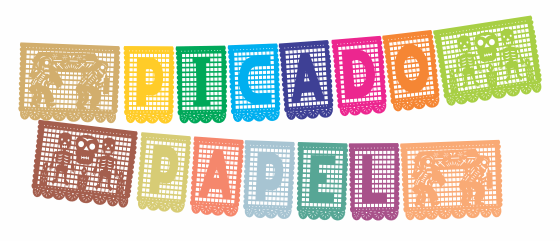
Esta fuente esta inspirada en el papel picado que se usa en México en festividades de Día de Muertos o en algunas fiestas de pueblos This font is inspired paper cutting used in Mexico on Day of the Dead festivities or in some towns parties |